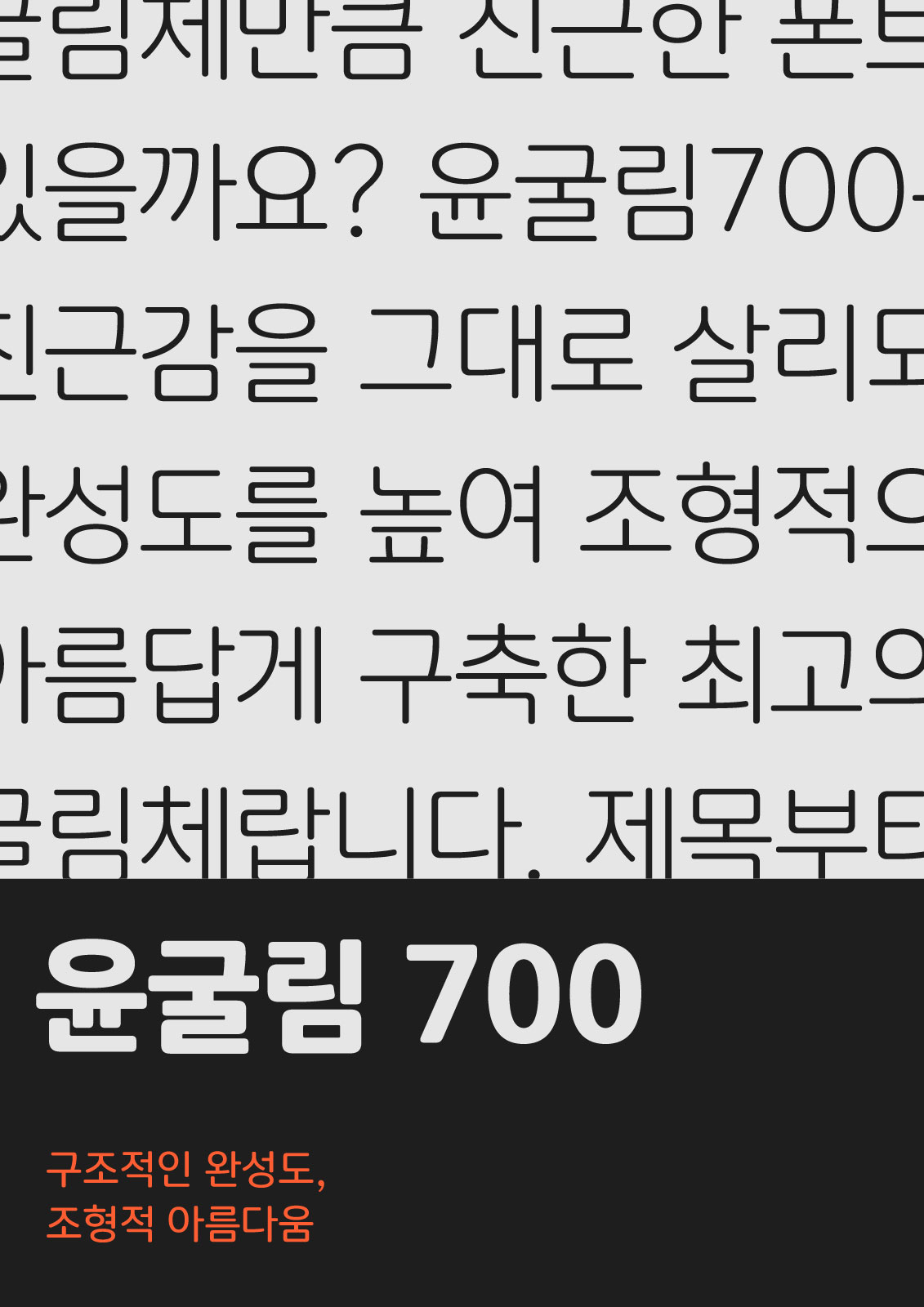
윤굴림700
Yoon 윤굴림700
굴림체만큼 친근한 폰트가 또 있을까요? 윤굴림700은 그 친근감을 그대로 살리되 구조적인 완성도를 높여 조형적으로 아름답게 구축한 최고의 굴림체랍니다. 제목부터 본문까지 제약 없이 사용할 수 있도록 아홉 단계의 굵기로 제작했으니, 언제, 어디서나 윤굴림과 함께하세요.